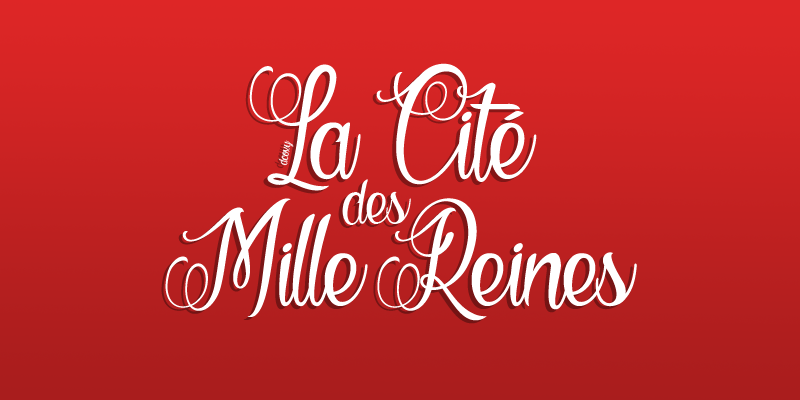
A fonte ‘La Cité des Mille Reines Font’ é uma escolha perfeita para quem busca uma elegância única ao adicionar detalhes únicos a qualquer projeto. Com sua inspiração na cultura francesa, essa fonte oferece um visual único e envolvente que pode ser usado em materiais de marketing ou comunicação gráfica. Através da chamada à atenção do seu designer, Hamilton, cada caractere parece uma pedra filosofal, repleta de nuances sutis e detalhes impressionantes. Esta fonte é perfeita para criar um toque singular em materiais como cartazes, logotipos ou revistas. Ela se destaca quando usada para títulos chamativos ou subtítulos importantes, destacando o design do seu trabalho de forma única. Com uma personalidade vibrante e um design cuidadosamente elaborado, ‘La Cité des Mille Reines Font’ é perfeitamente adaptável a qualquer estilo, desde gráficos rústicos até designs modernos e sofisticados. Com o contato prévio, você pode adquirir as licenças necessárias para uso comercial e promocional. Não espere mais – este é um excelente ponto de partida para destacar seu trabalho de design.